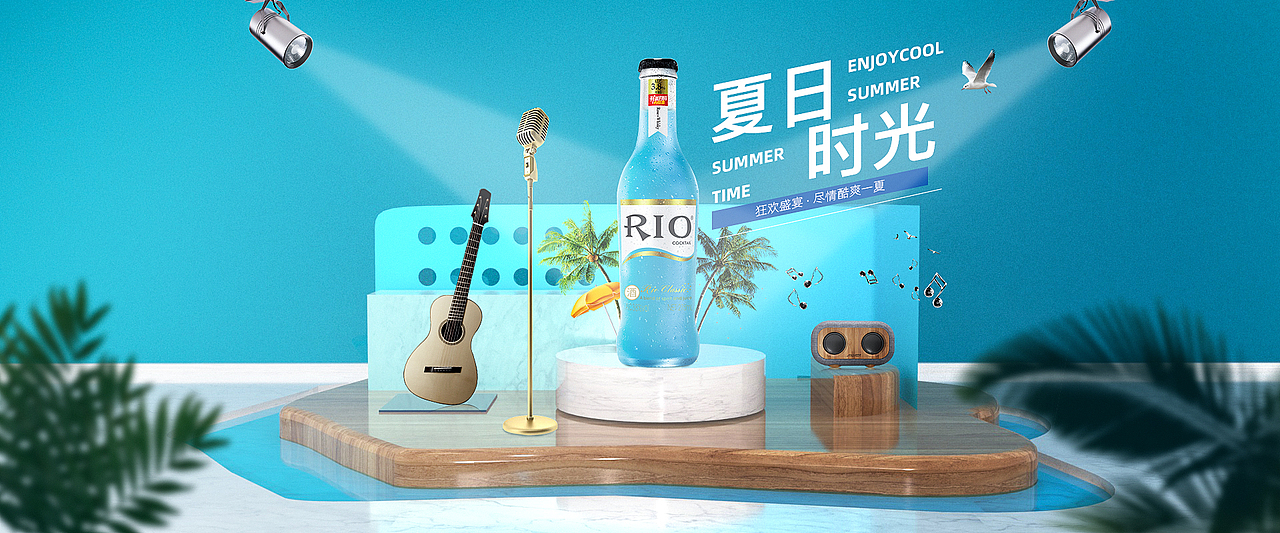
电商banner练习
近期对海报设计的配色与排版有了一些新的思考,做了一些练习。
卡其色的衣服搭配会给人温柔的感觉,但颜色搭配不好容易让人感觉平淡无感,因此左侧标题和购买按钮以纯白突显引导成交。
夏天比较炎热,所以整体采用了冷色调,倾斜的字体给画面活泼的感觉,用音乐体现产品清爽的口感。泳池、麦克风、射灯等元素让消费者置身酒吧派对。